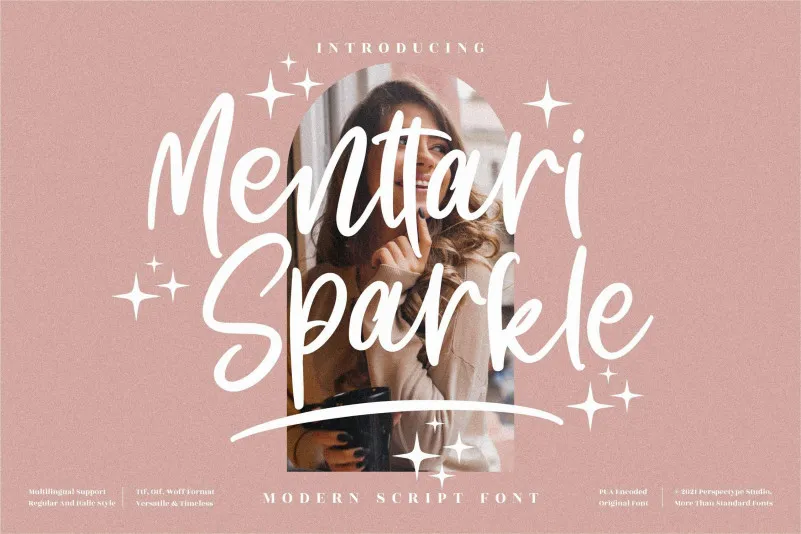
Aqui está uma versão adaptada para a descrição solicitada do download da font ‘Menttari Sparkle Font’, que se encaixa perfeitamente com sua categoria de script fonts criada pelo designer perspectype: “Mentaliza-se no charme e na relaxação desta fonte script, chamada Menttari Sparkle. Ela transpira sofisticação e elegância. A fonte exala uma sensação leve, quase descontraída, que combina perfeitamente com qualquer projeto. O estilo alternativo e as ligaturas da fonte tornam-na a escolha ideal para qualquer tipo de trabalho gráfico: desde rótulos de produtos até textos de marketing digital. Suas linhas suaves, combinadas à sua estética elegante, permitem que você personalize seu layout com facilidade. Adquira essa fonte agora e adicione um toque único a seus projetos – seja para impressão ou digital. Menttari Sparkle é uma escolha perfeita para quem busca charme e sofisticação em sua tipografia.”